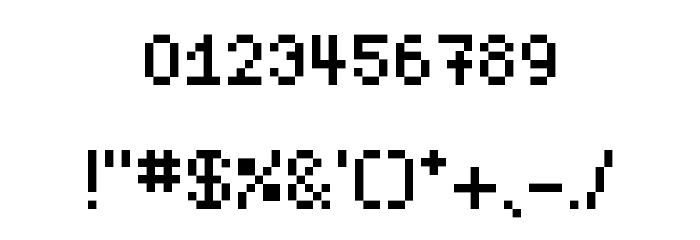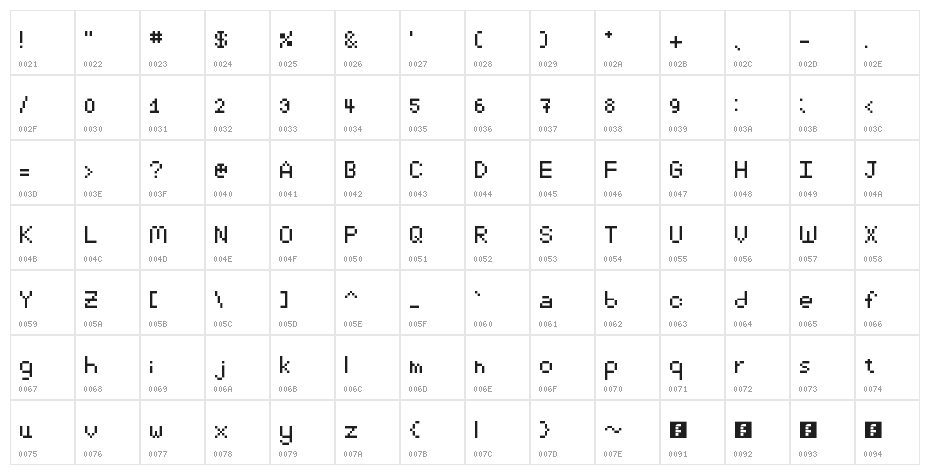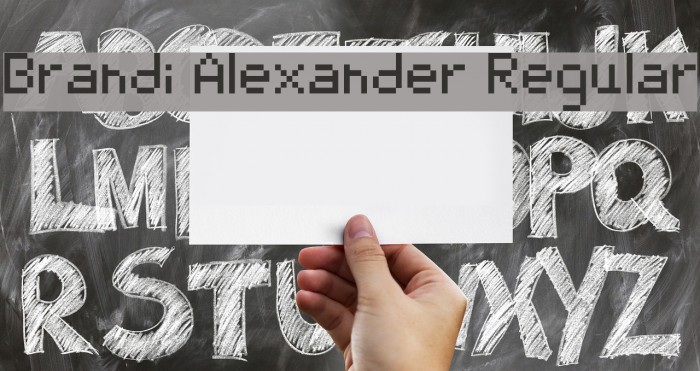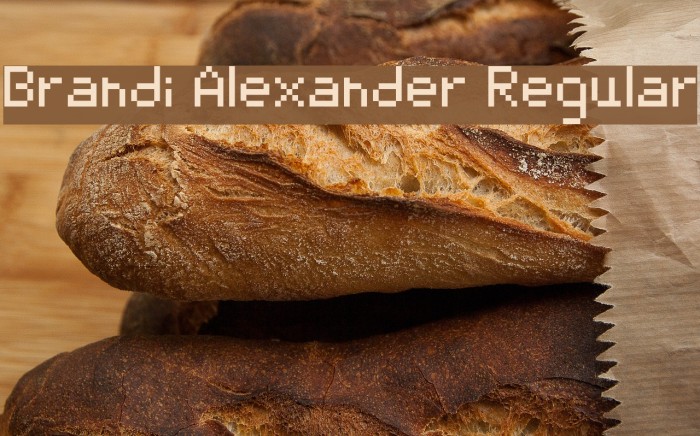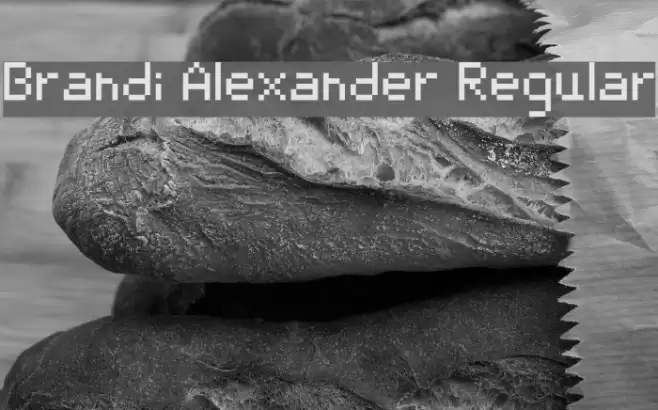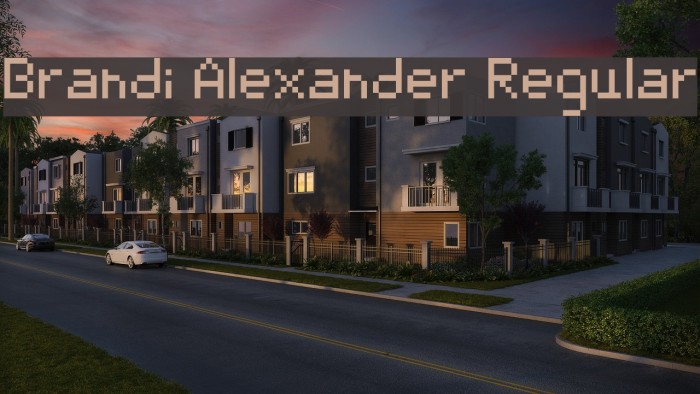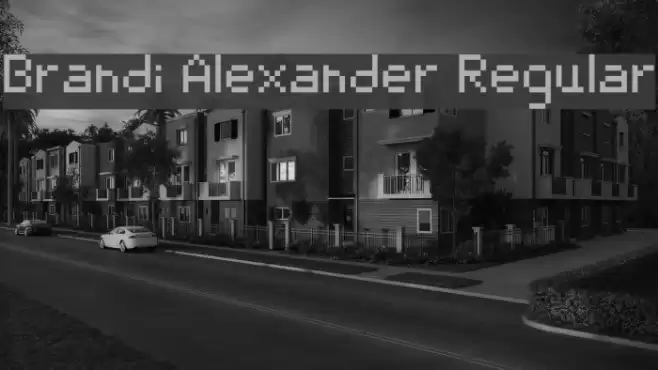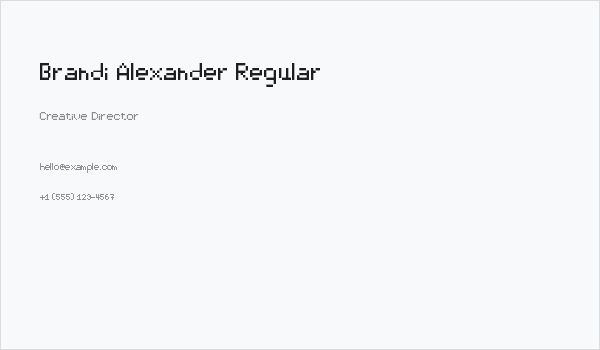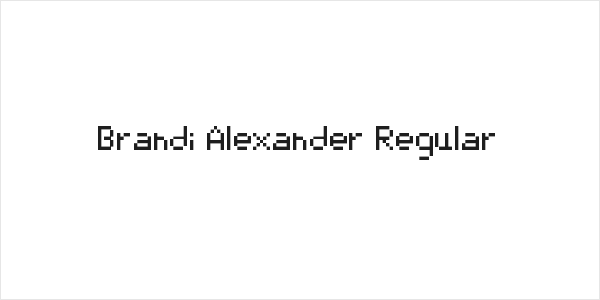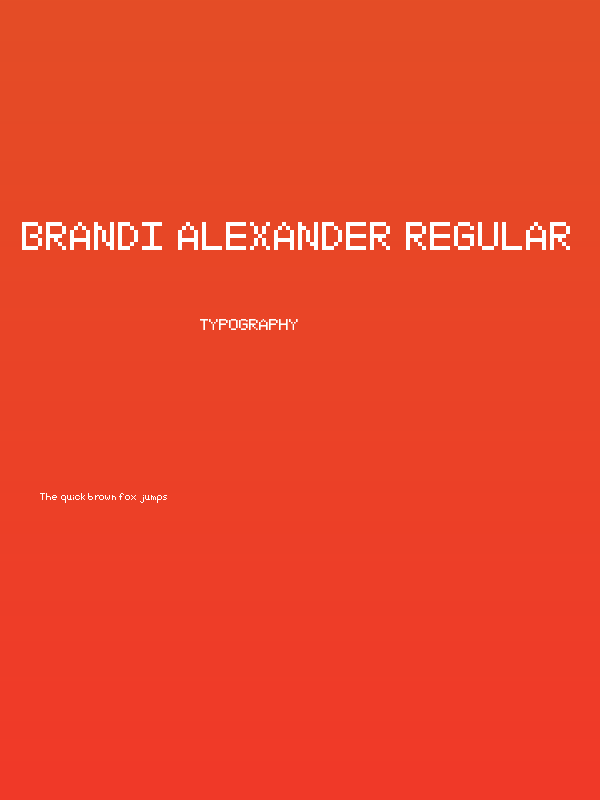
Brandi Alexander Regular Font
✎ Pixel
| Style général | Retro, Digital |
| Projets proposés | Ideal for retro video game designs, tech-themed posters, digital art, and nostalgic branding projects. |